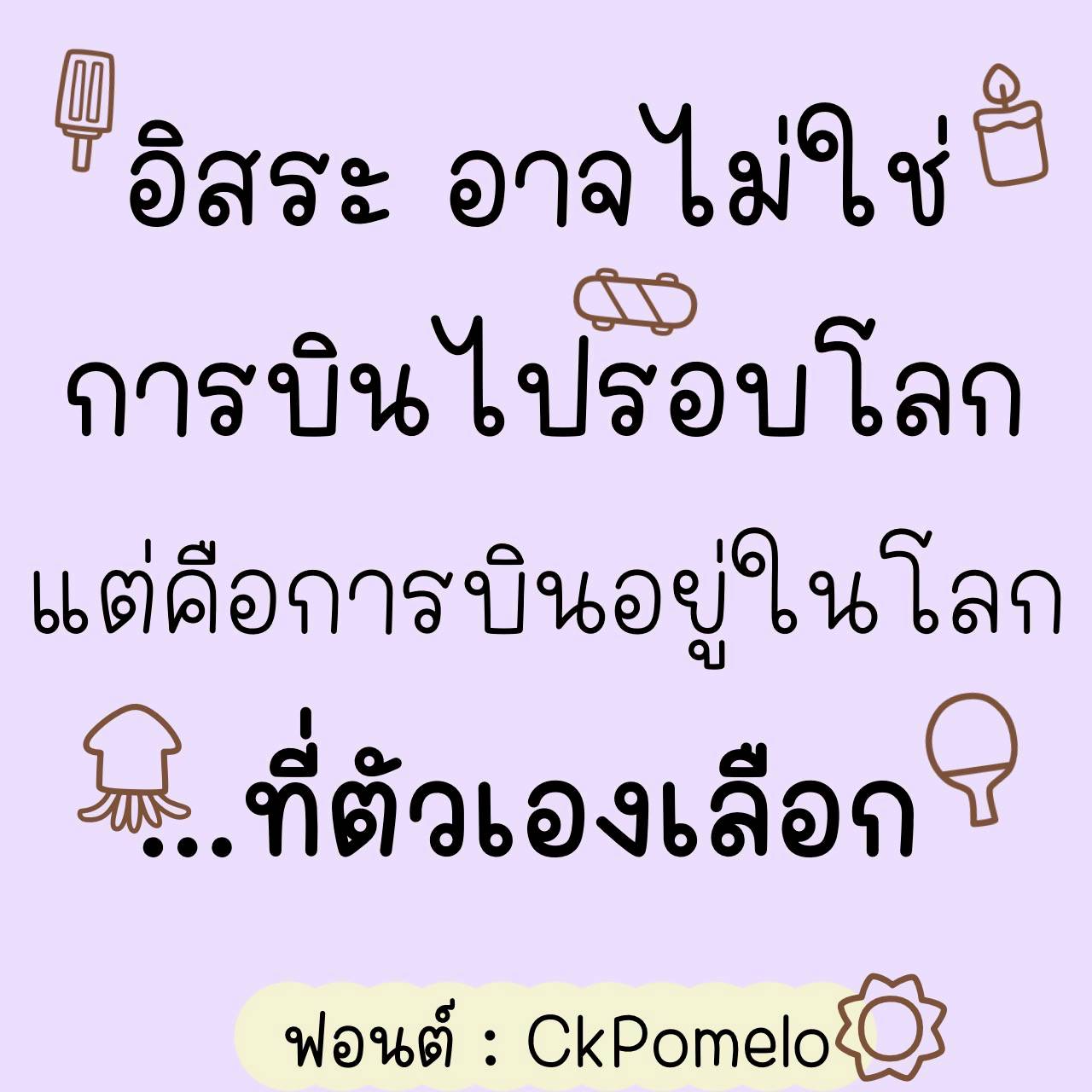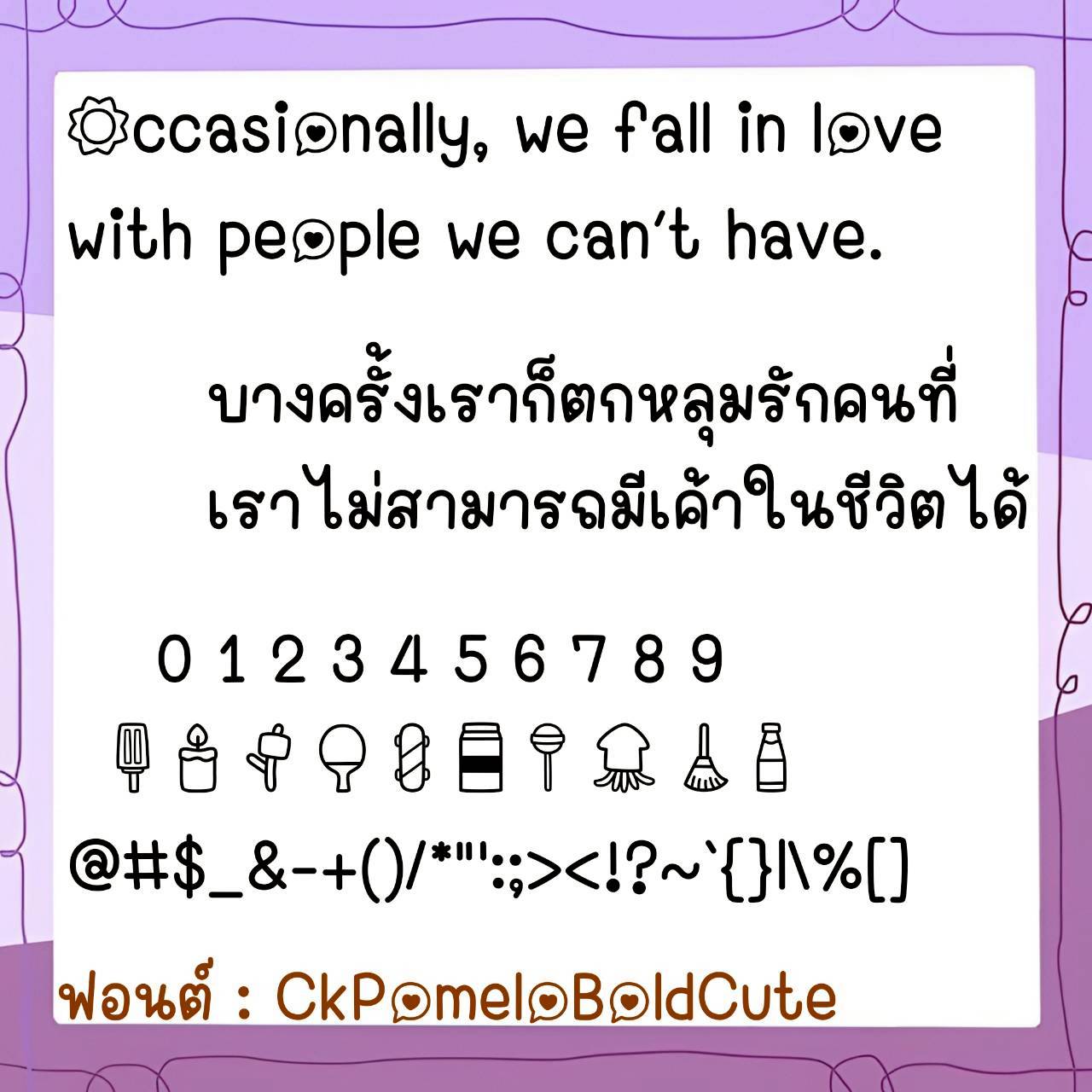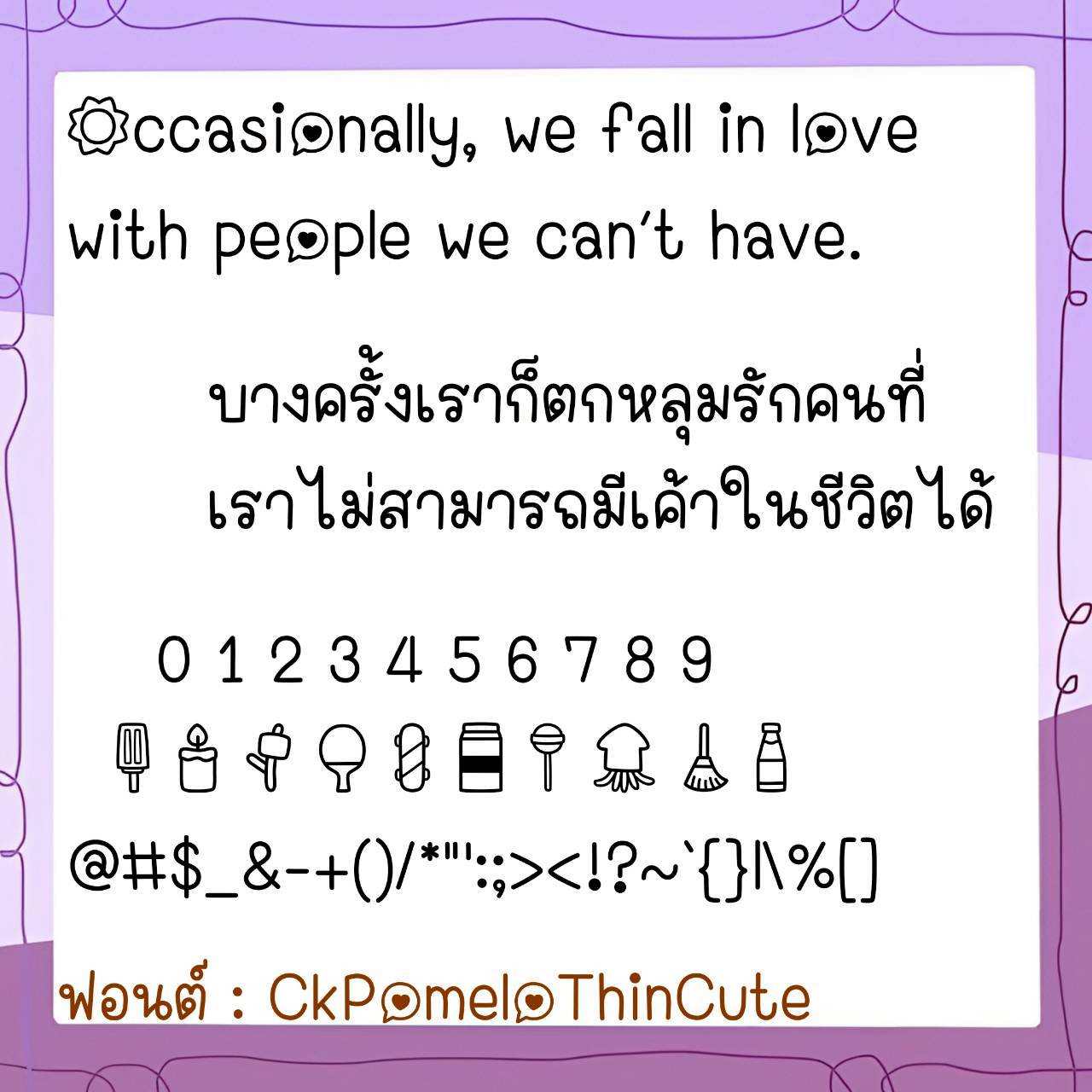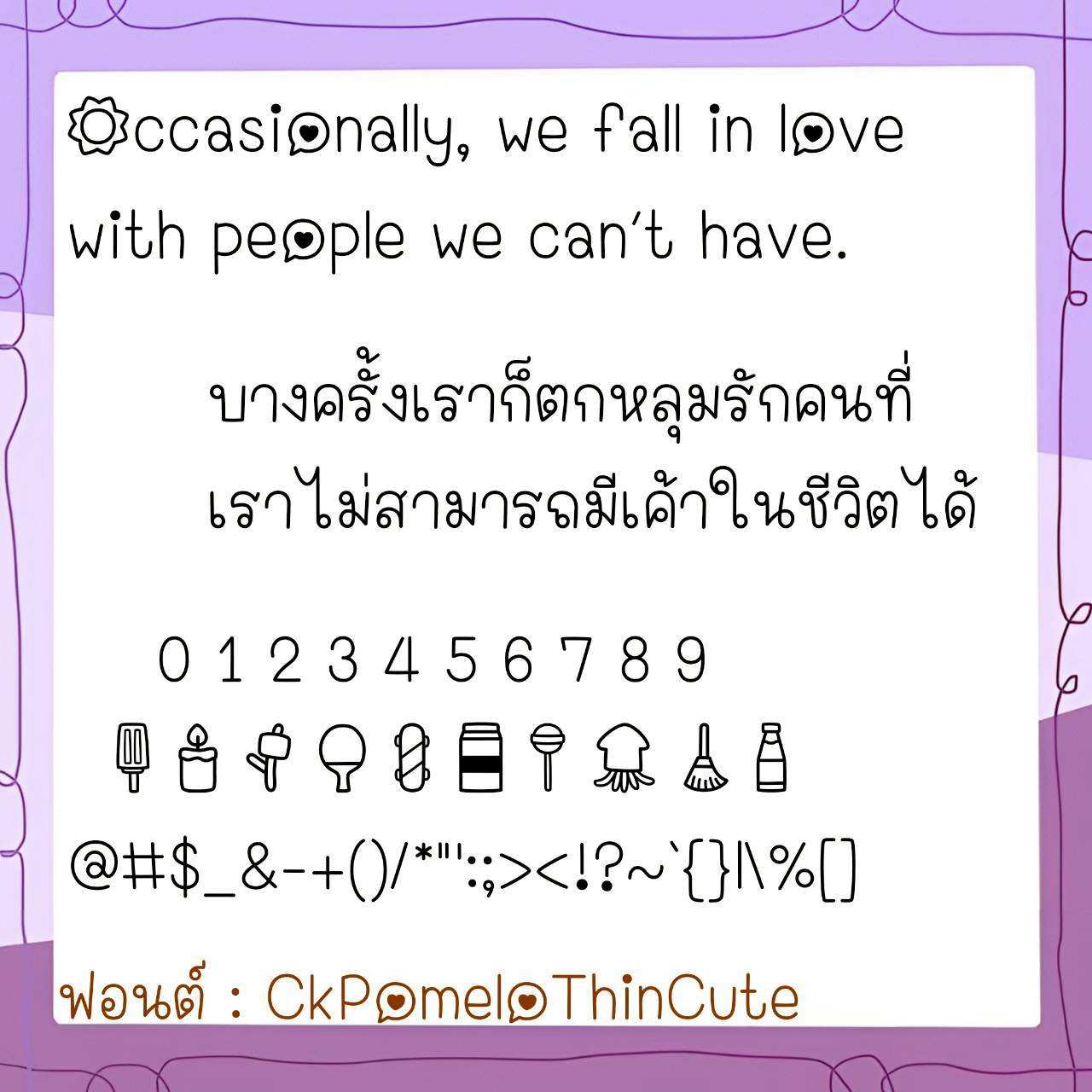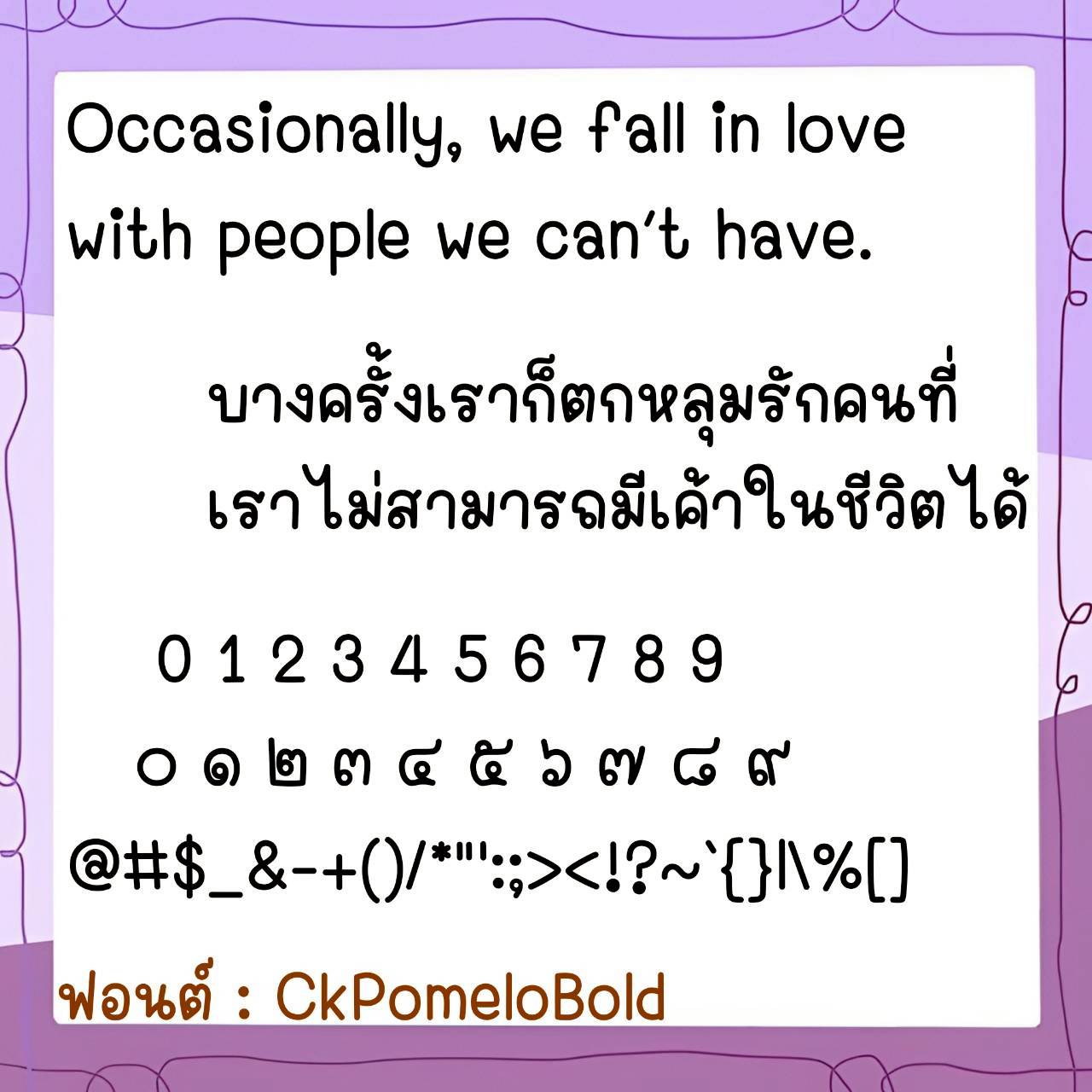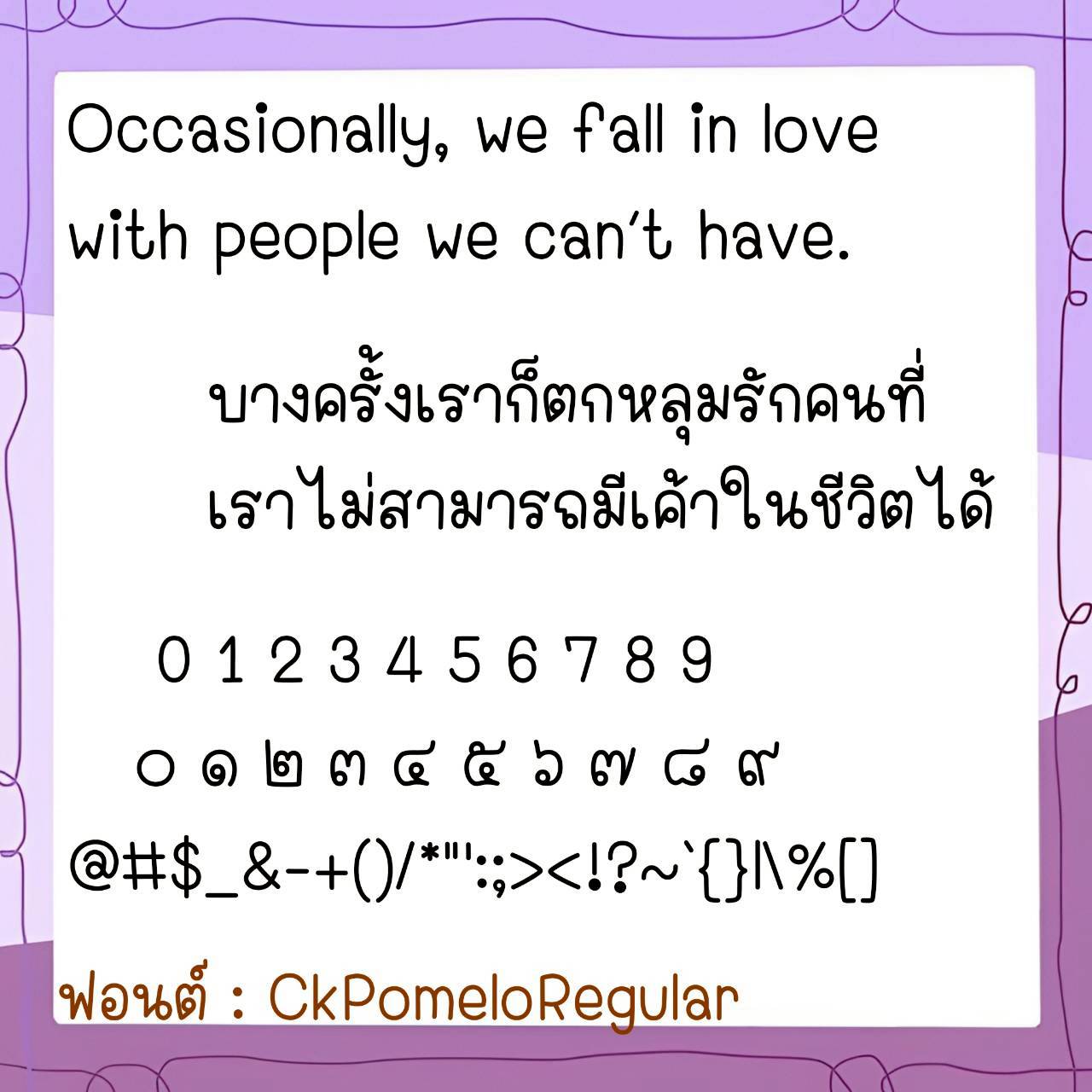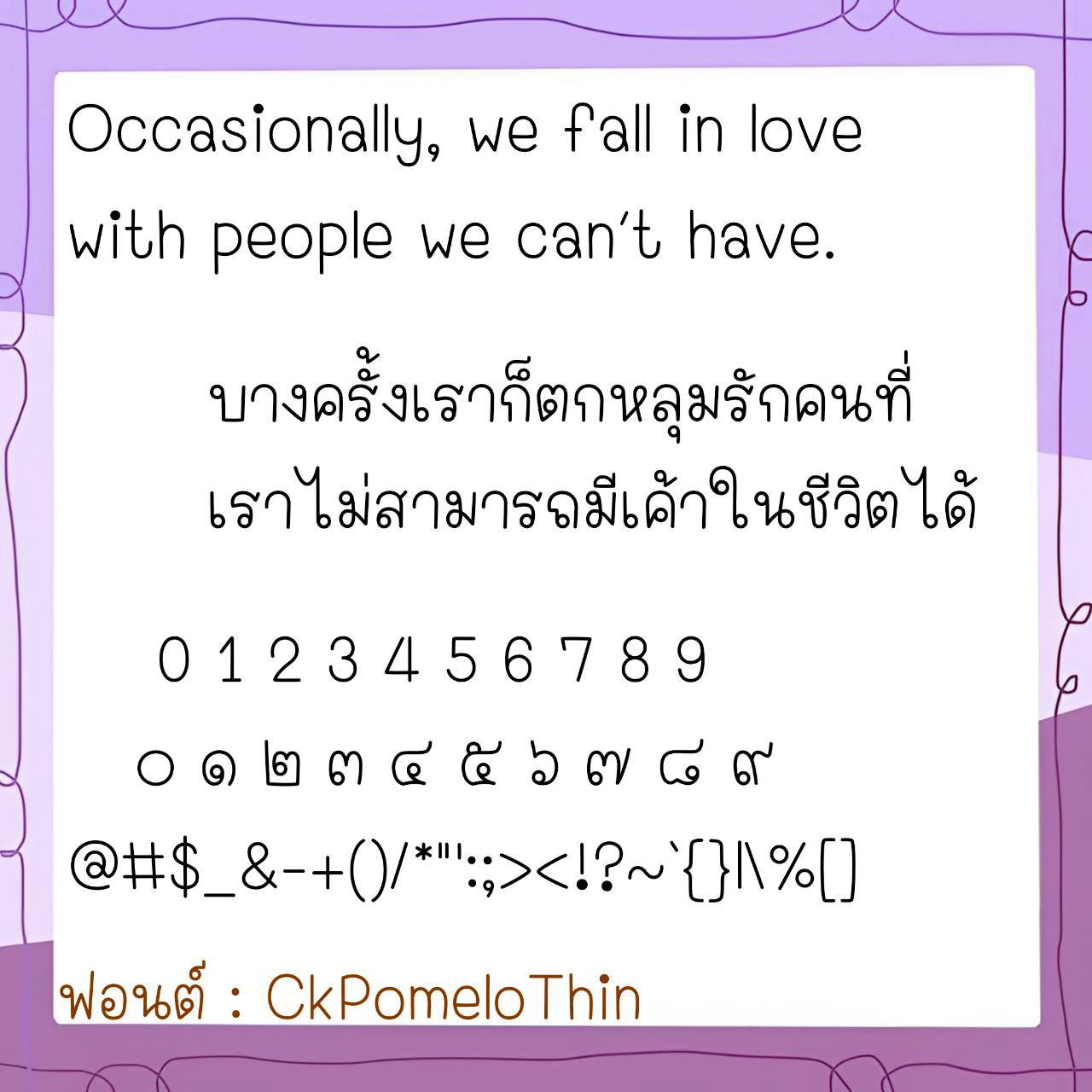
Font CkPomelo
ชื่อสินค้า : Font CkPomelo 💙
🔸 ฟอนต์ลายมือแนวน่ารัก สไตล์วัยรุ่นนิดๆ เน้นอ่านง่ายสบายตา ใช้งานได้หลากหลายแนว และยังมีไฟล์อิโมจิน่ารักๆ ที่ใช้แทนเลขไทยให้ด้วยค่ะ 🥰💙
🔹 A cute handwritten font with a youthful style. It’s easy to read and easy on the eyes. It can be used in many different styles. It also includes cute emoji files that can be used in place of Thai numerals. 🥰💙